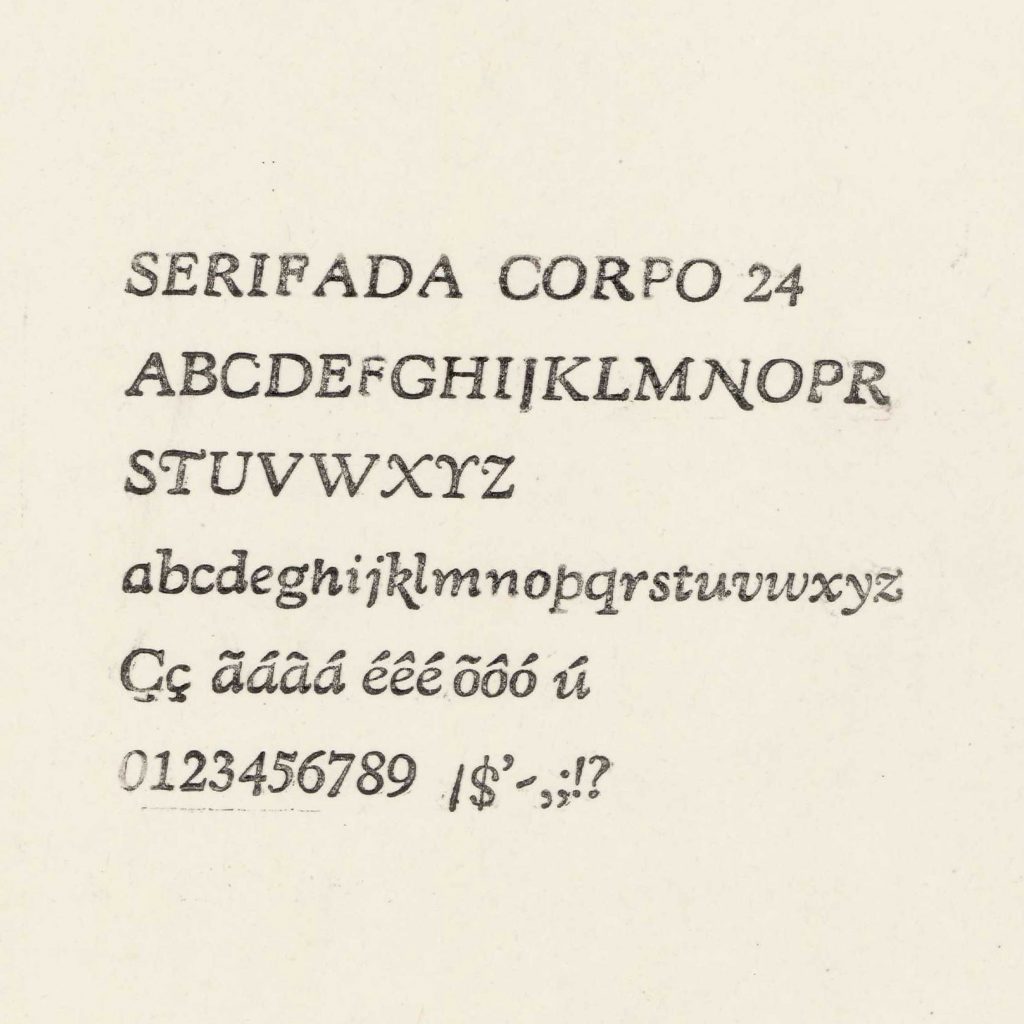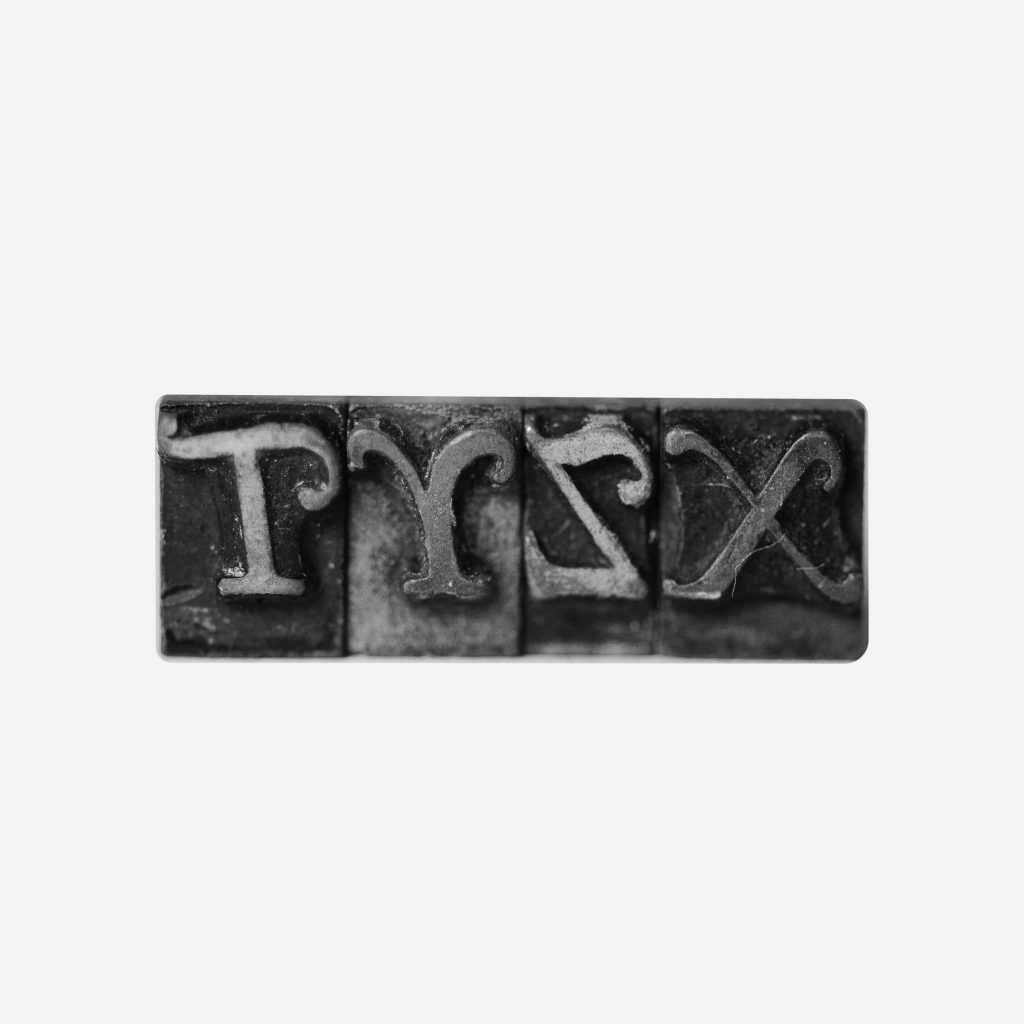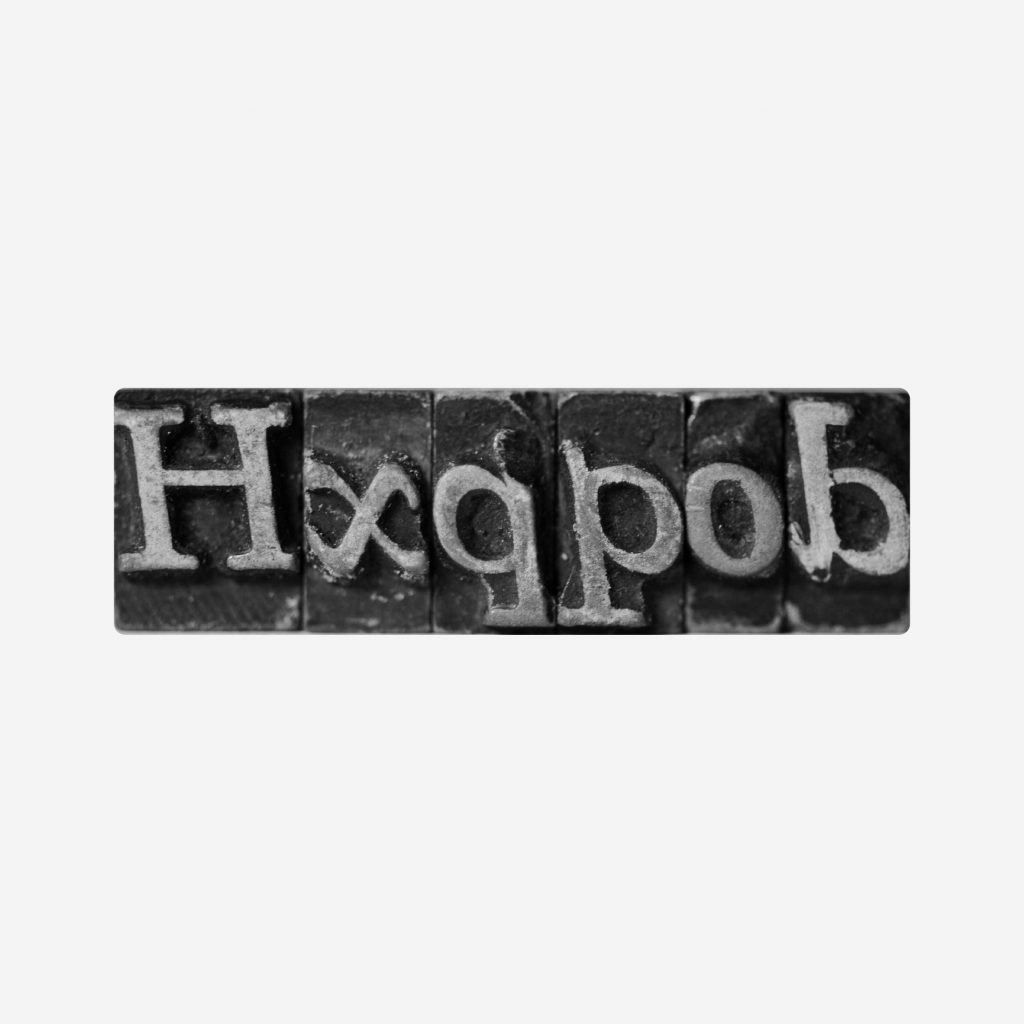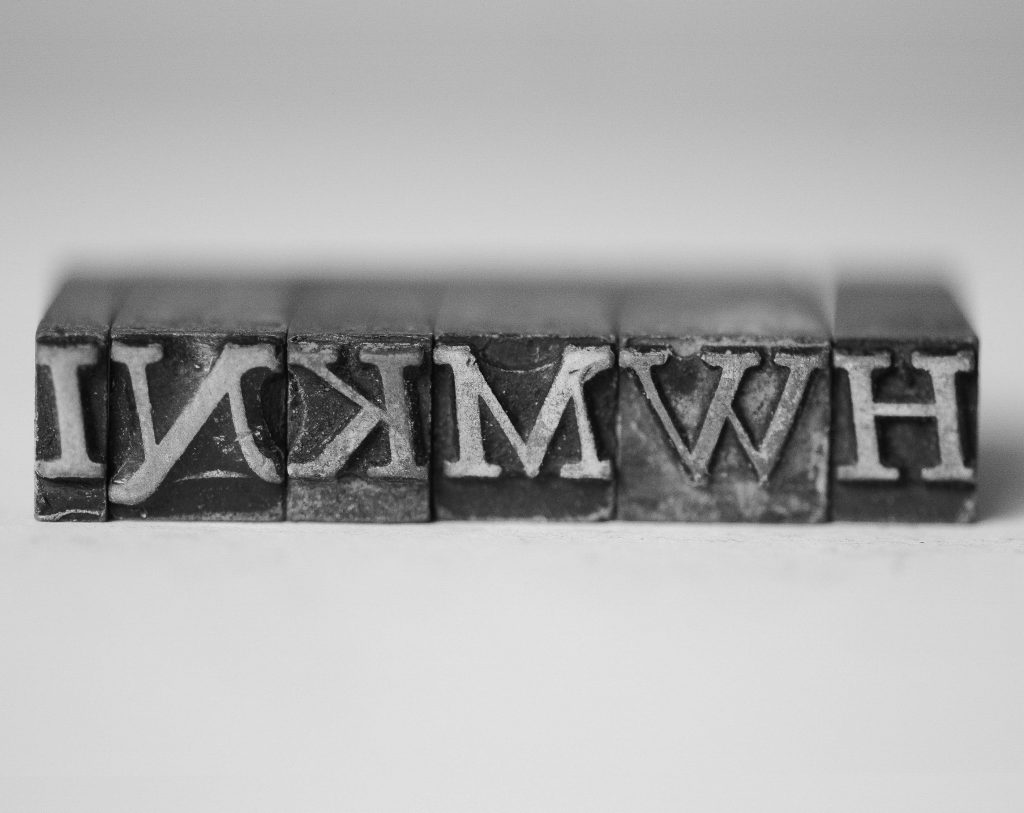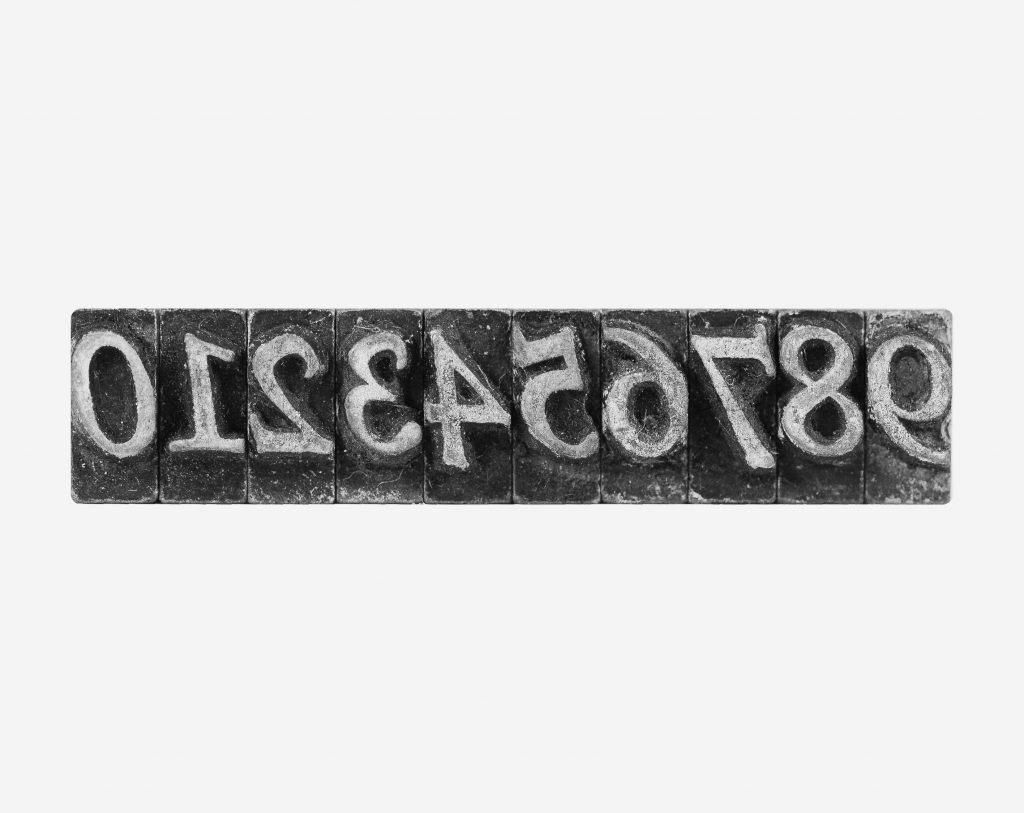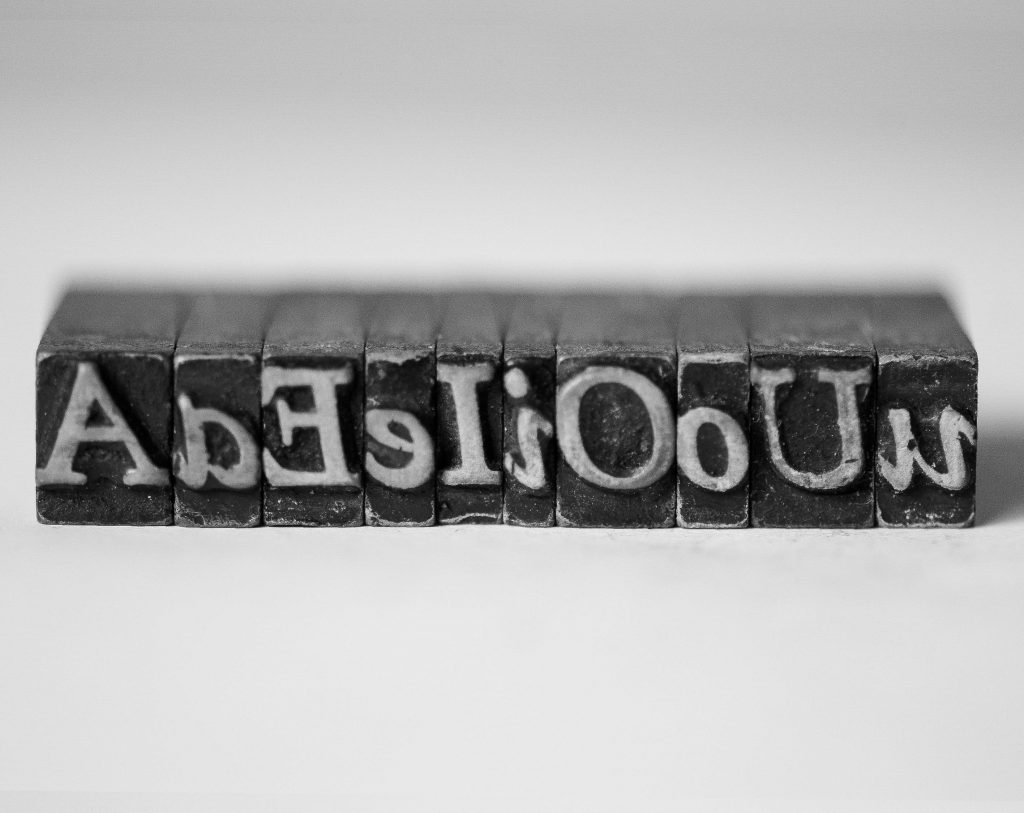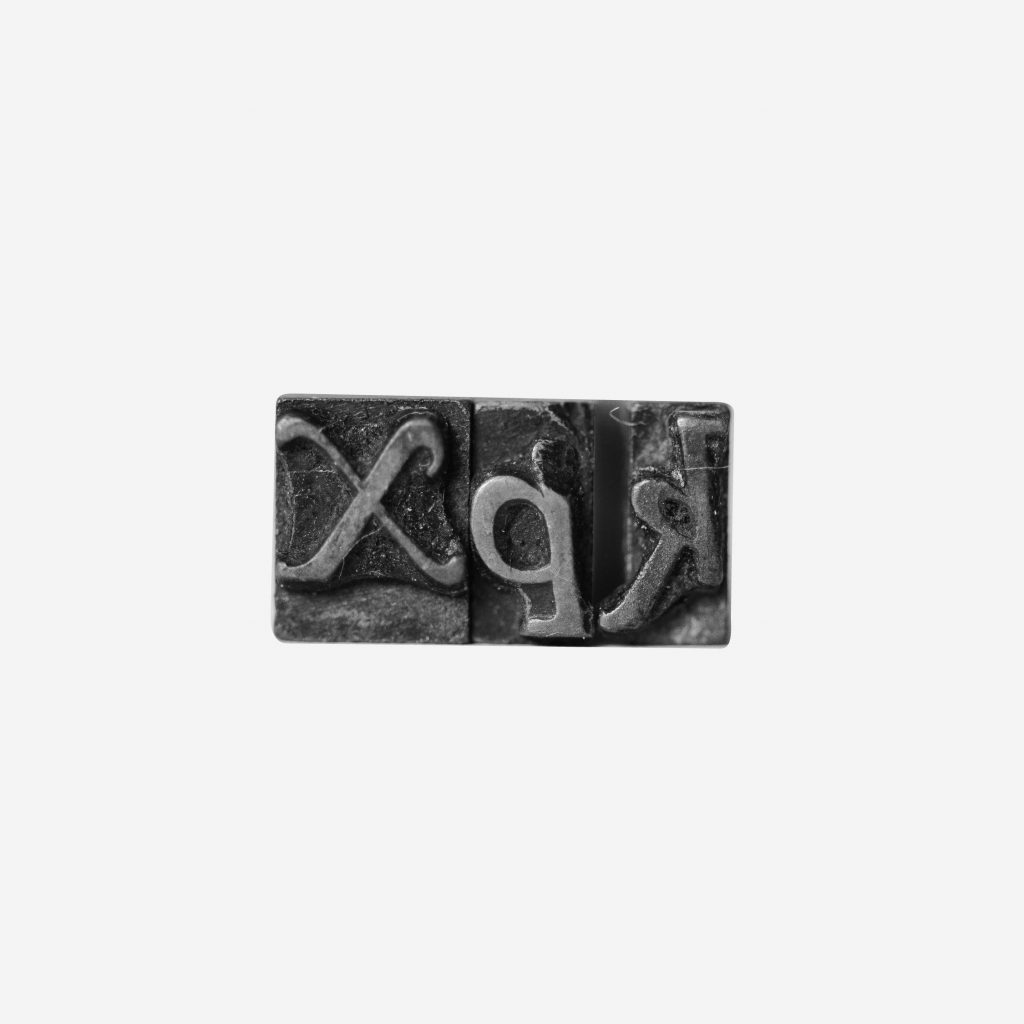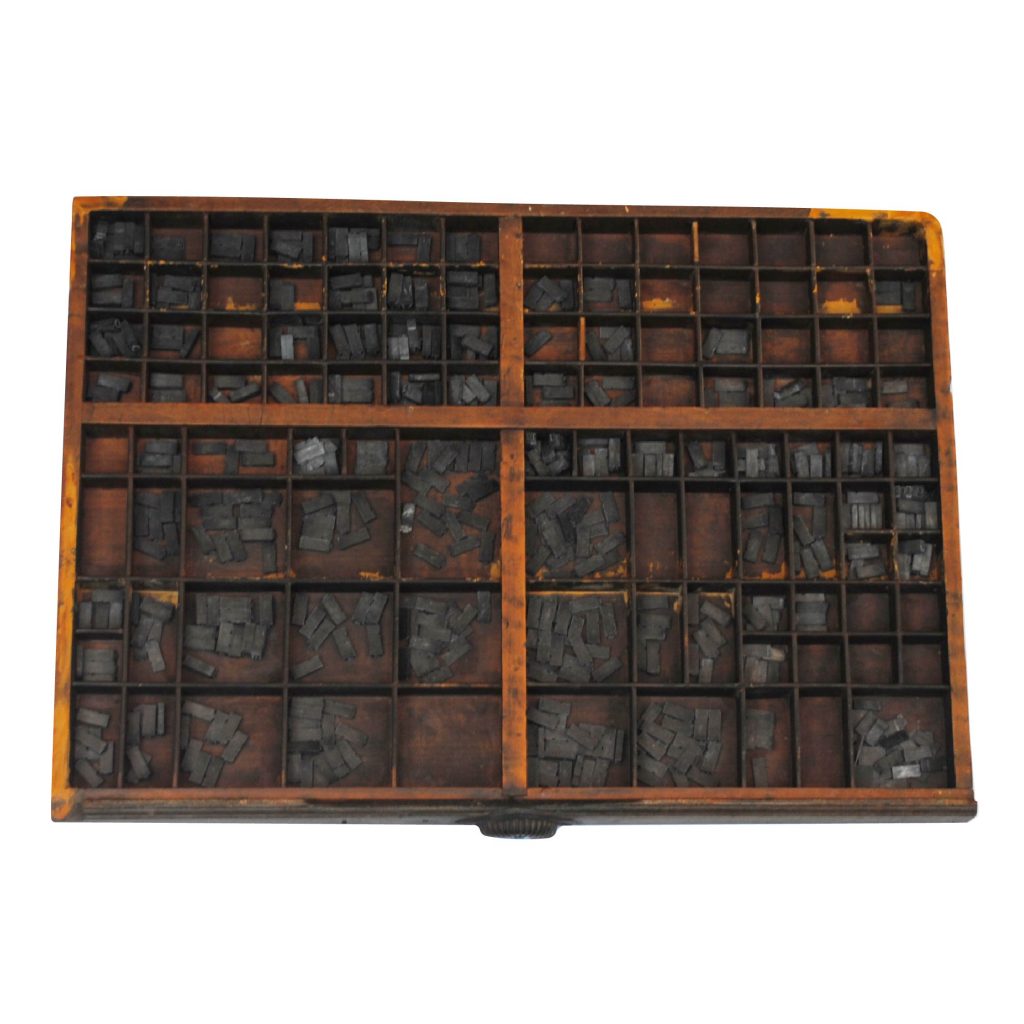
[Kennerley Bold (Goudy) Nº 269-1] 24pt
Estilo
Serifada
Caracteres Chave
N, T, Q, g, k, p, v, z
Marcas de uso recorrente; alguns tipos apresentam desgaste na face que pode comprometer a qualidade da impressão.
Maiúsculas | Minúsculas | Algumas maiúsculas acentuadas | Algumas minúsculas acentuadas | Numerais | Ligaturas | Sinais | Pontuações
Faltam acentuadas de algumas letras, como Íí, Ìì,Îî, Óó, Úú, Ûû.
História do Estilo
Foi encontrada a fonte Kennerley Bold em um catálogo denominado Tipo: Monotipo (Cia Lanston do Brasil, 1968), uma filial da Monotype do Brasil, que se assemelha com o formato e estilo dos caracteres presentes na gaveta. Sem possuir uma marca de origem nos tipos, não foi possível definir sua procedência. Segundo Fonts in Use (s.d.), a fonte Kennerley foi desenhada por Frederic W. Goudy (EUA, 1865 – 1947) em 1911 para um livro publicado por Mitchell Kennerley. Em 1924, Goudy adicionou os estilos bold e bold itálico a pedido da Monotype (série 269/2691), empresa que detinha os direitos da fonte desde 1920.
Observações do Pesquisador
Tratam-se de letras contrastadas e espessas.